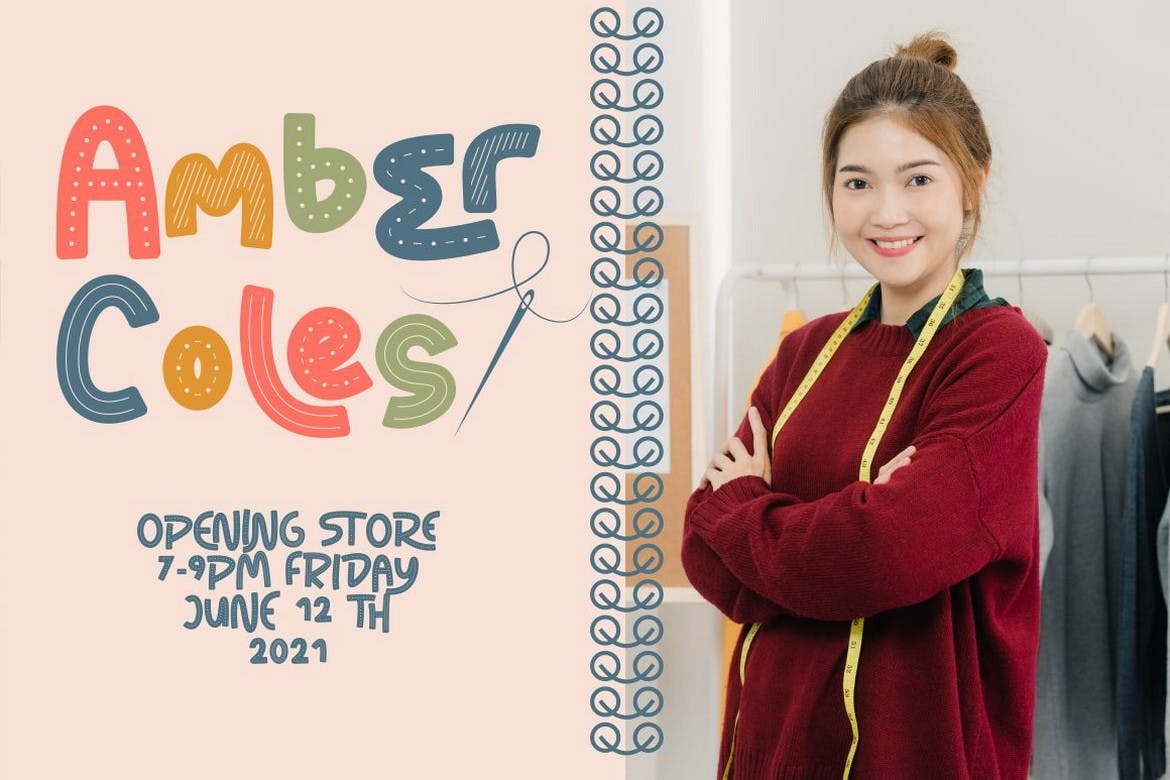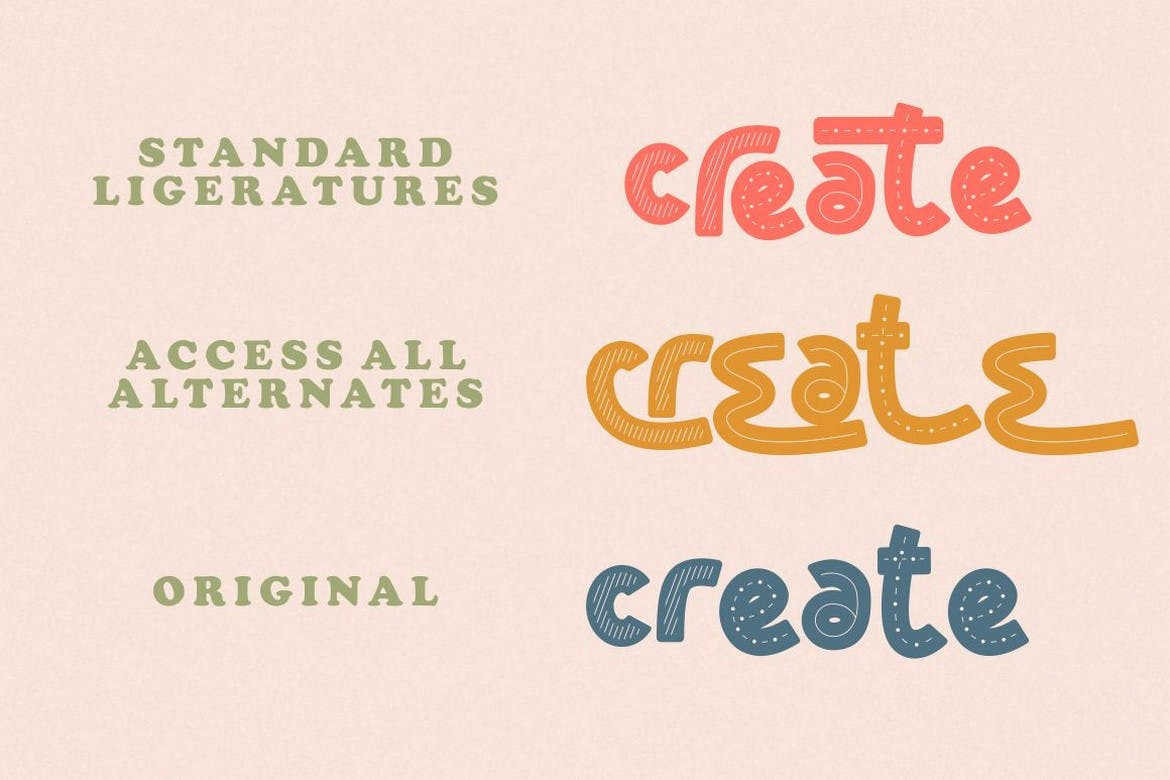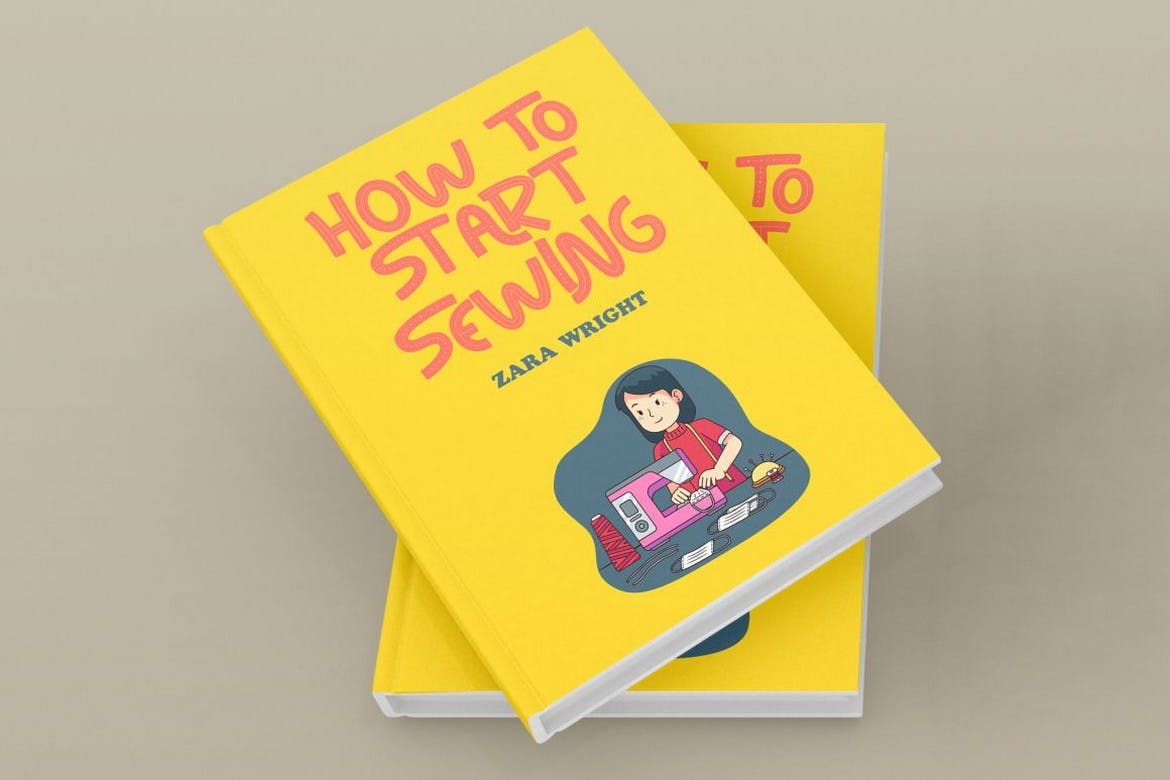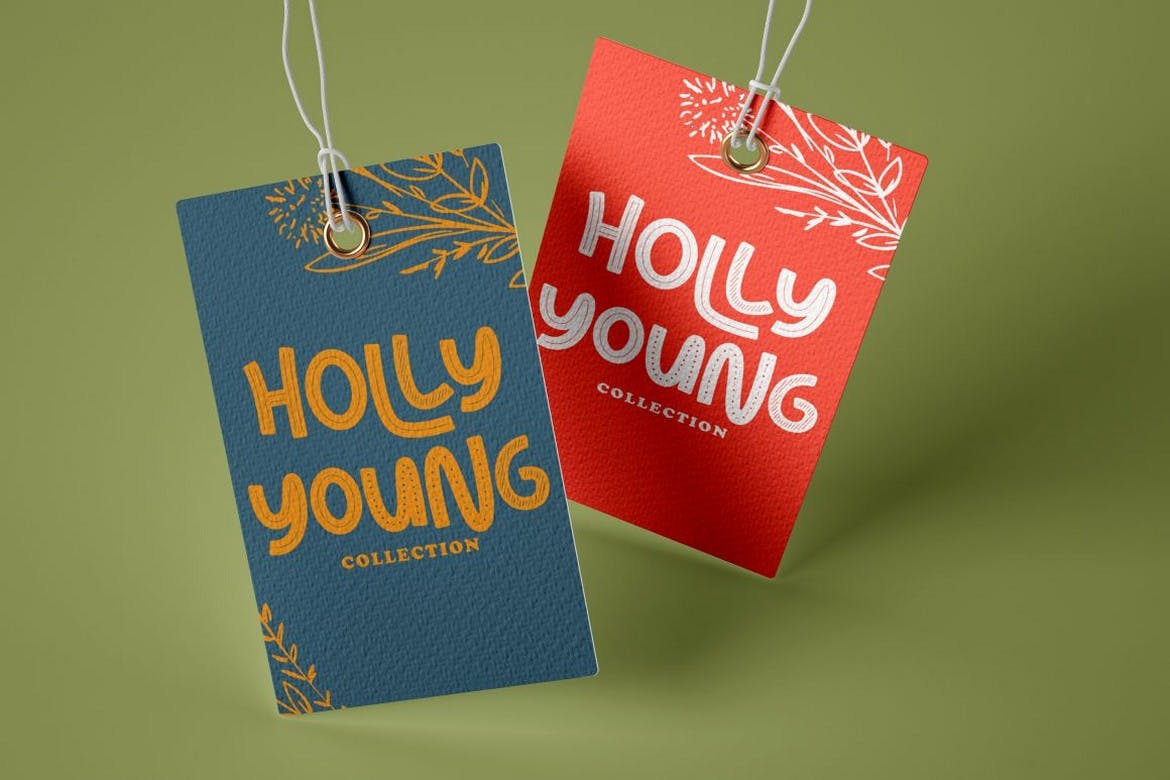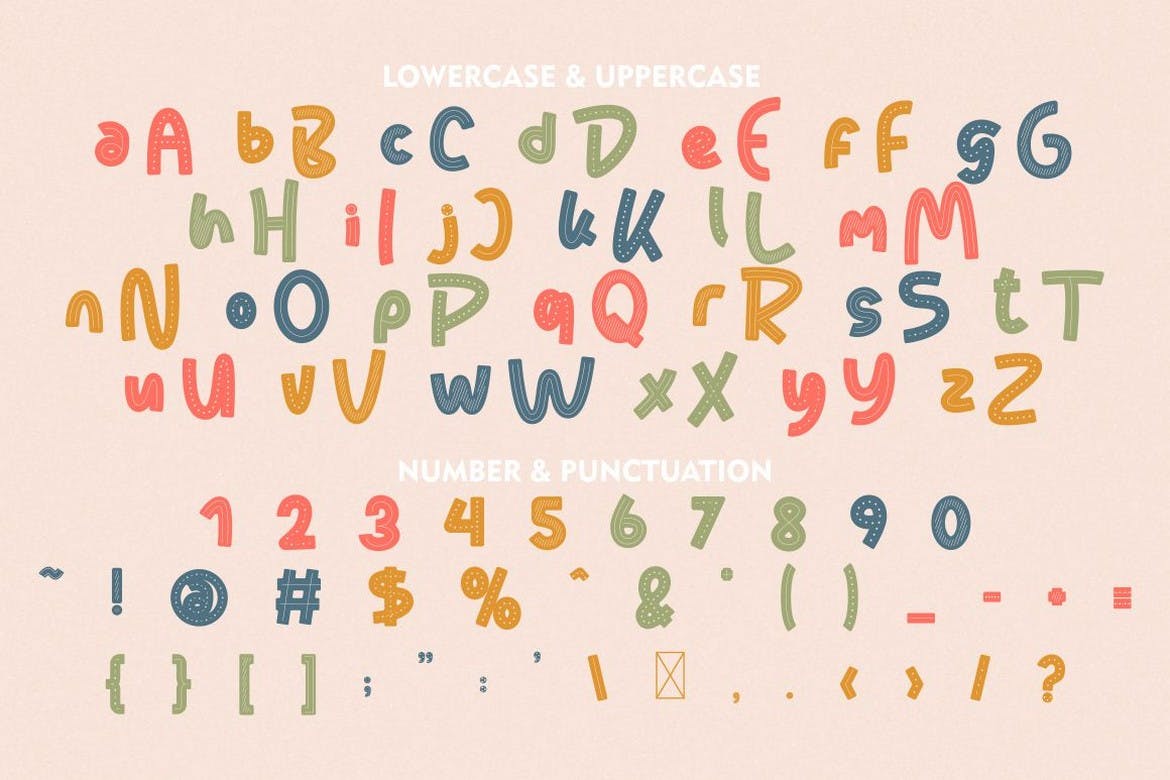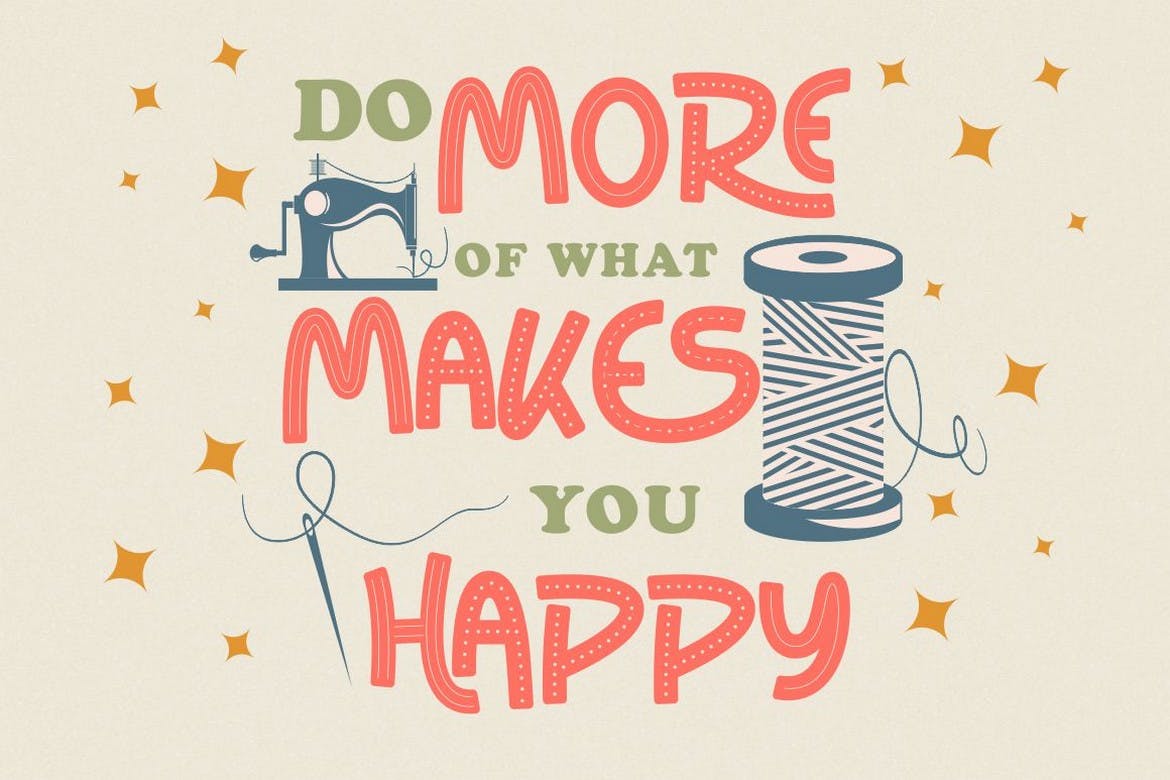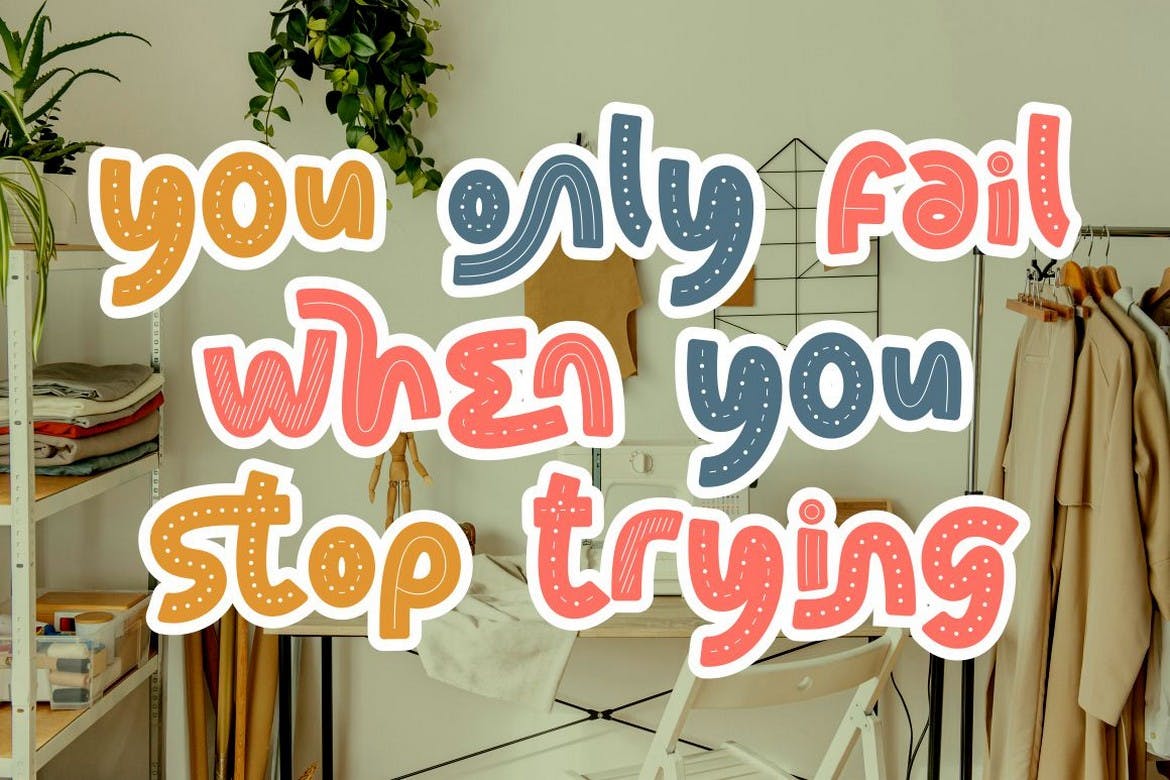
فونت Tailor Craft - Bold Quirky Display Font
فونت Tailor Craft یک فونت نمایشی Bold و جالب با شخصیتهای جذاب و مد روز است.
با سبک کودکانه خود، این فونت برای پروژههایی که به کودکان مربوط میشود بسیار مناسب است. از جمله کتابهای داستان، تصاویر، کتابهای کمیک، پوسترها، کارتهای تبریک، لوگوها، برندینگ، برچسبها، SVG و صنایع دستی.
حروف جایگزین در این فونت به چندین ویژگی Open Type تقسیم شدهاند که شامل Swash، Stylistic Sets، Stylistic Alternates، Contextual Alternates و Ligature میباشد. میتوانید به این ویژگیهای Open Type با استفاده از برنامههای حرفهای مانند Adobe Illustrator، Adobe InDesign، Adobe Photoshop، Corel Draw X و Microsoft Word دسترسی پیدا کنید. این فونت همچنین از چندین زبان پشتیبانی میکند.